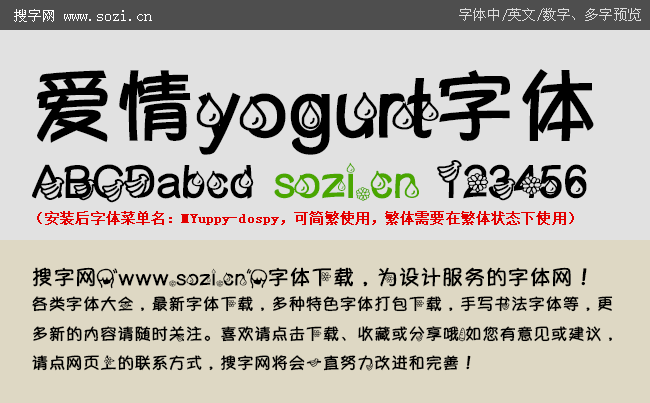
愛情yogurt字體
搜字網(wǎng)給大家提供一款很卡通的手機(jī)中文字體下載。修改者給這款字體叫愛情yogurt字體,這款手機(jī)中文字體以POP字體為原形,在筆畫間嵌入卡通圖形,該中文字體趣味性強(qiáng),又保持了文字的識(shí)別度,非常適合喜歡卡通的朋友在手機(jī)上安裝使用。